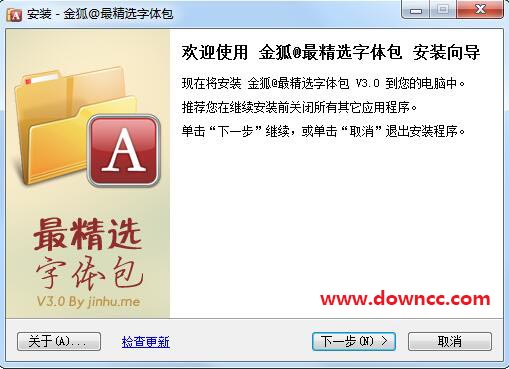
金狐精華字體包一共包含了408款最新的字體,字體分類明確,可以適用于設計、印刷、辦公等行業(yè)使用!能夠滿足多數(shù)用戶的不同字體需求!歡迎用戶在綠色資源網下載使用!
金狐精華字體包是一款經典的字體應用,這款最新版本的字體包是從三千多款各類字體里精挑細選,錄用408款,而且新包字體分類更加詳細,適合從事網頁設計、辦公排版等行業(yè)用戶使用!
1.金狐精選字體這次更新作了比較大的調整,歷時一周左右,從三千多款各類字體里精挑細選,錄用408款,并根據字體的不同特點作了更詳細的分類。
2.包括“簡 體中文字體(91款)”、“繁體中文字體(18款)”、“精選英文字體(213款)”、“硬筆書法字體(9款)”、“數(shù)學公式字體(24款)”、“拼音樂 譜字體(10款)”、“圖案圖形字體(31款)”、“經典像素字體(12款)”。
3.能夠輕松應對日常辦公排版,亦能很大程度上滿足網頁設計和 文印等專業(yè)設計的需求。